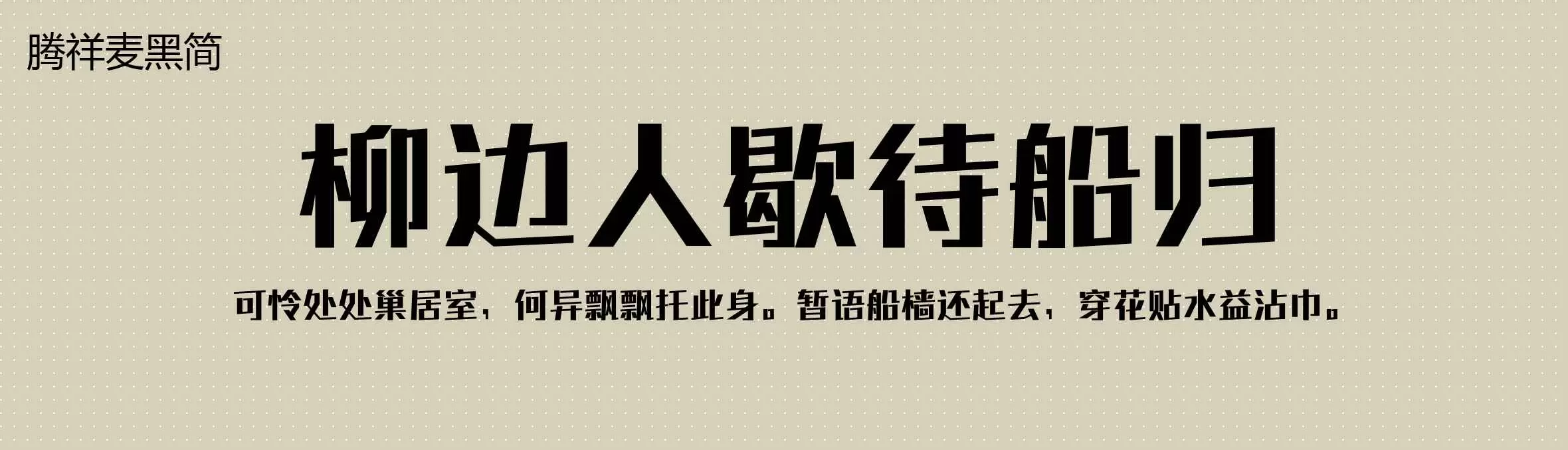
腾祥麦黑字体是腾祥公司自主精心设计开发的美术黑体。首次创新将黑体类字形的横笔画做了斜上的设计,突显手写字体横笔画斜上的视觉效果,横笔画斜而字不倒,字形端庄、严谨,给用户带来一种全新的字体应用体验。字体风格:横笔画斜上,撇、捺、点、折、勾均采用极简的直笔画,无任何圆弧修饰,所以字形刚硬、简洁。因部分撇、捺、点为斜横加菱形,酷似丰收的麦穗,故取名为麦黑。 适用于标题、广告设计等。